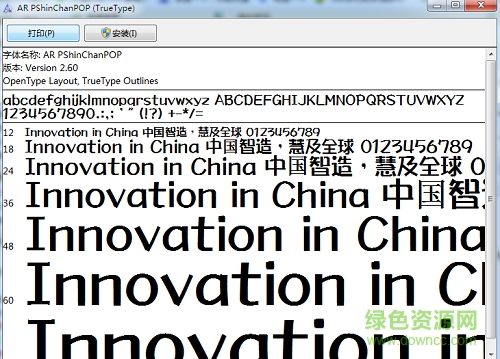
文鼎新潮pop體是文鼎打造的一款非常有個(gè)性的中文字體,給人圓潤(rùn)的感覺(jué),制造了一種古典的意境,有喜歡的朋友歡迎來(lái)綠色資源網(wǎng)免費(fèi)下載使用!
文鼎新潮pop簡(jiǎn)體是一款很適合用于美工設(shè)計(jì)方面的字體,本字體圓潤(rùn)耐看,非常漂亮,筆畫(huà)干凈純粹毫無(wú)多余點(diǎn)綴,布白得當(dāng),既具有書(shū)法藝術(shù)性又不失實(shí)用性!